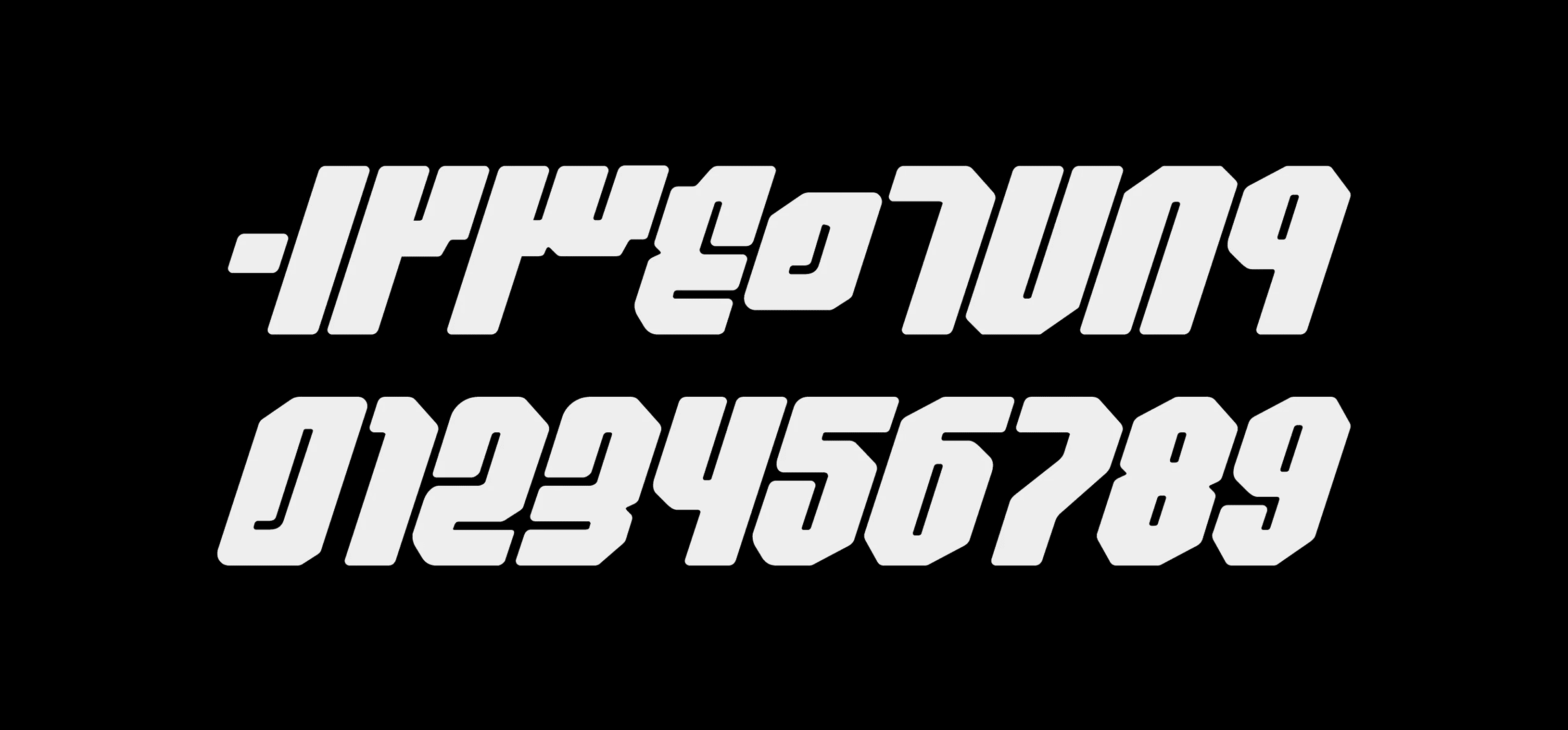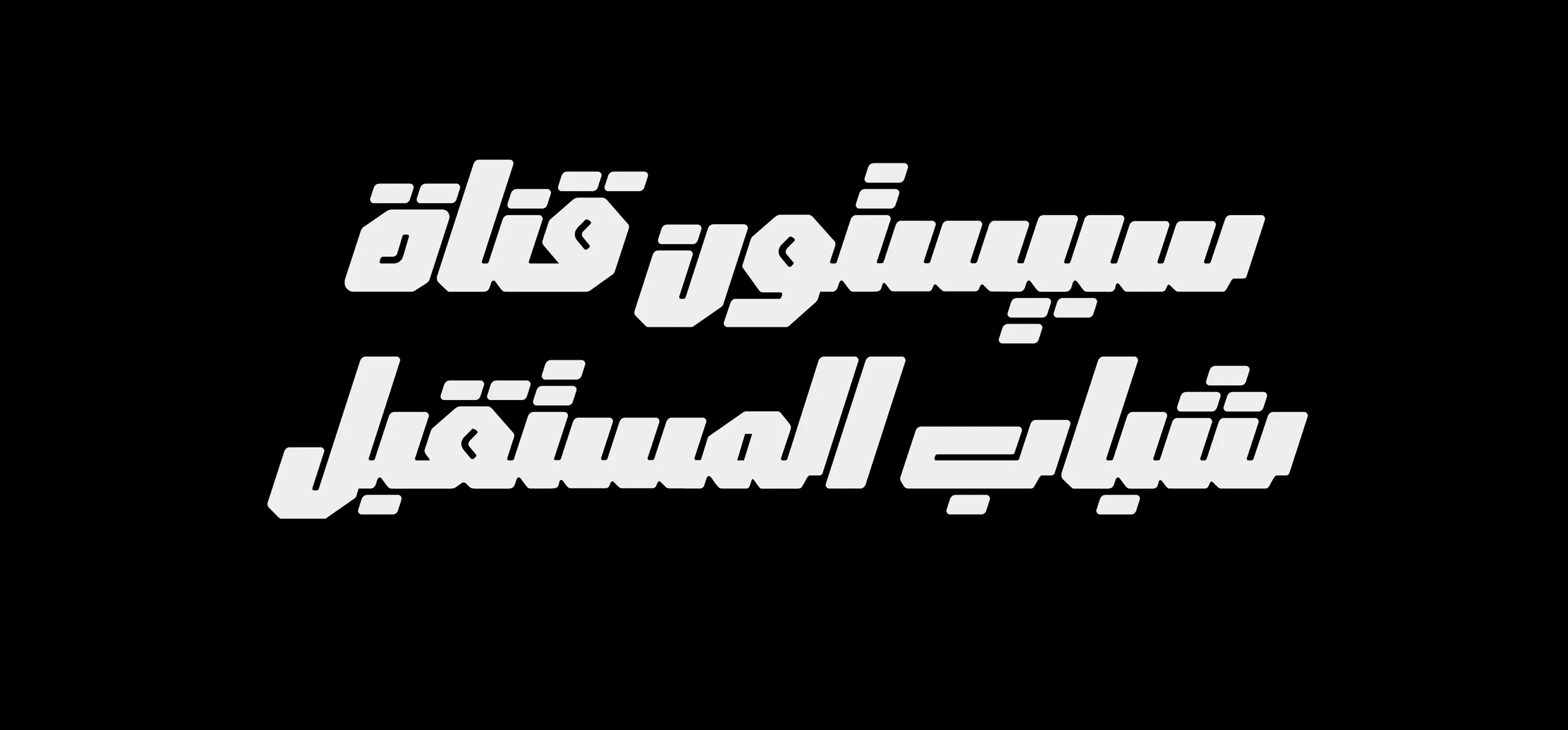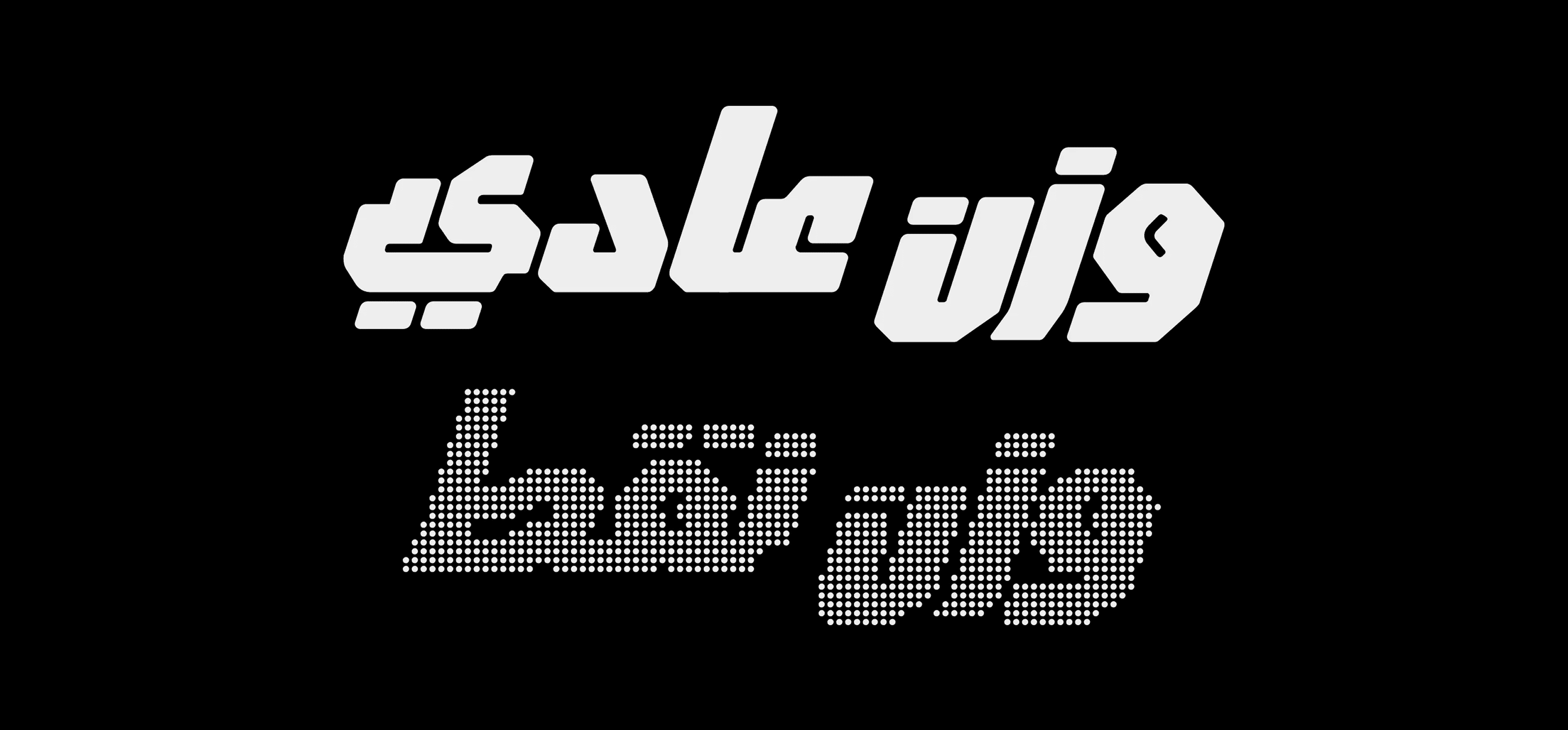
زَعفَران – Zafran
زَعفَران هو خط عرض صناعي أنيق يتميز بانحناءات جذابة وزوايا حادة، ويمنح إحساسًا مائلاً (Oblique) مع فراغات موحّدة تخلق محاذاة دقيقة ومنظمة. يجمع الخط بين الطابع الجمالي والصرامة التصميمية، مما يجعله مثاليًا للعناوين البارزة والتصاميم العصرية.
زَعفَران – Zafran
زَعفَران هو خط عرض صناعي أنيق يتميز بانحناءات جذابة وزوايا حادة، ويمنح إحساسًا مائلاً (Oblique) مع فراغات موحّدة تخلق محاذاة دقيقة ومنظمة. يجمع الخط بين الطابع الجمالي والصرامة التصميمية، مما يجعله مثاليًا للعناوين البارزة والتصاميم العصرية.
زَعفَران – Zafran
زَعفَران هو خط عرض صناعي أنيق يتميز بانحناءات جذابة وزوايا حادة، ويمنح إحساسًا مائلاً (Oblique) مع فراغات موحّدة تخلق محاذاة دقيقة ومنظمة. يجمع الخط بين الطابع الجمالي والصرامة التصميمية، مما يجعله مثاليًا للعناوين البارزة والتصاميم العصرية.